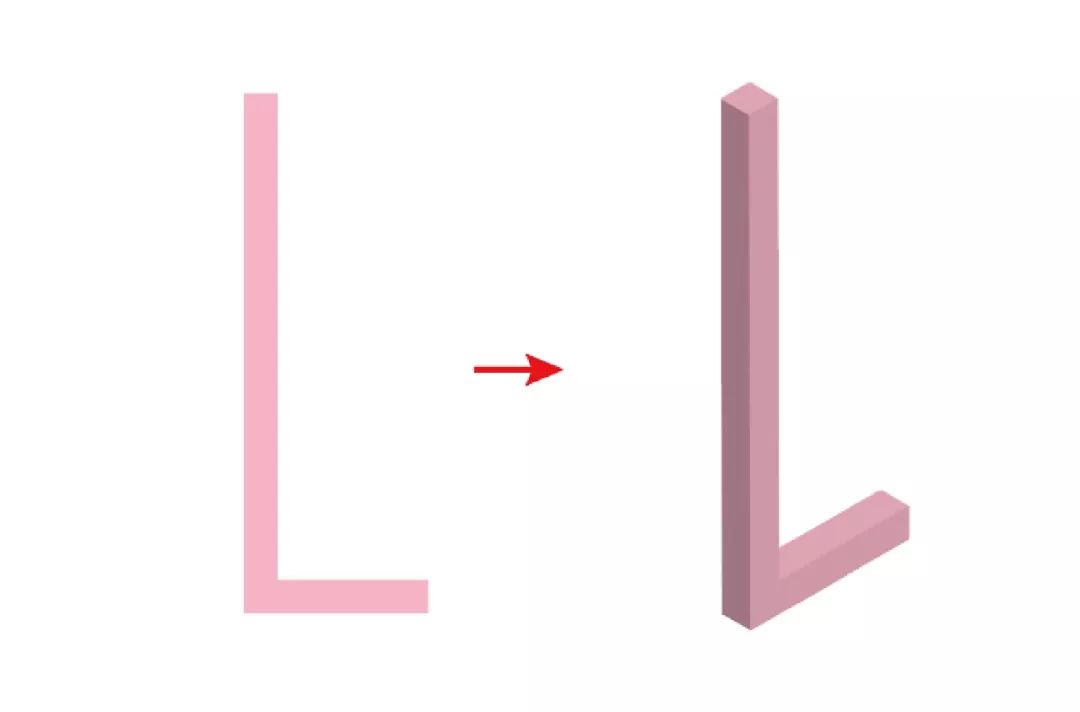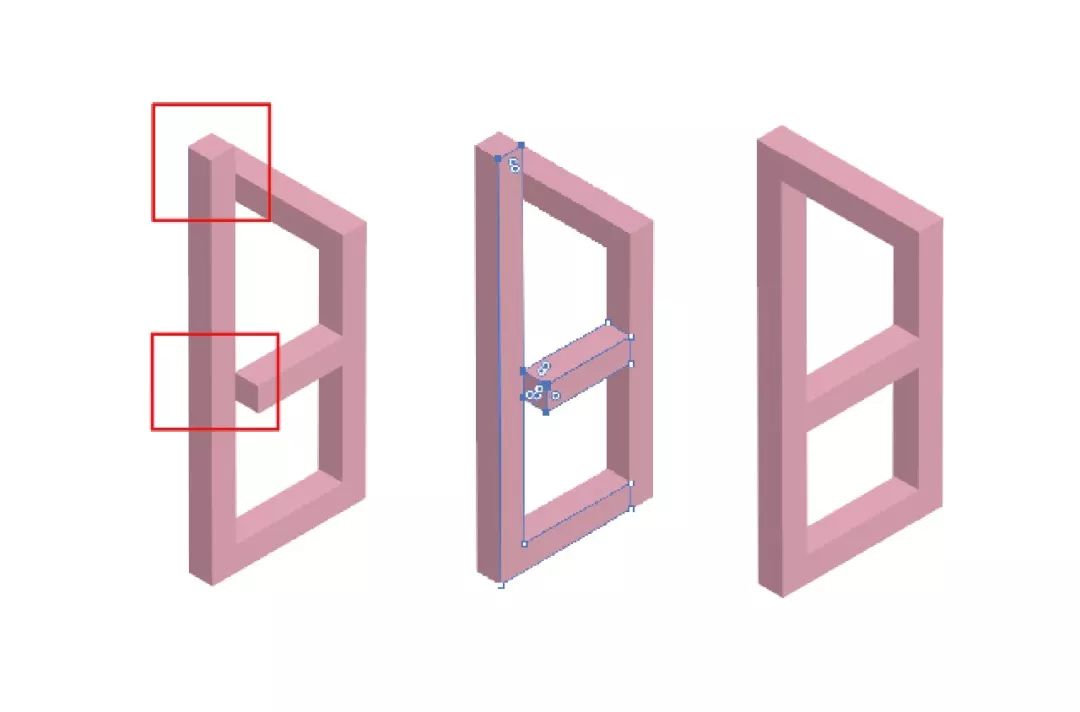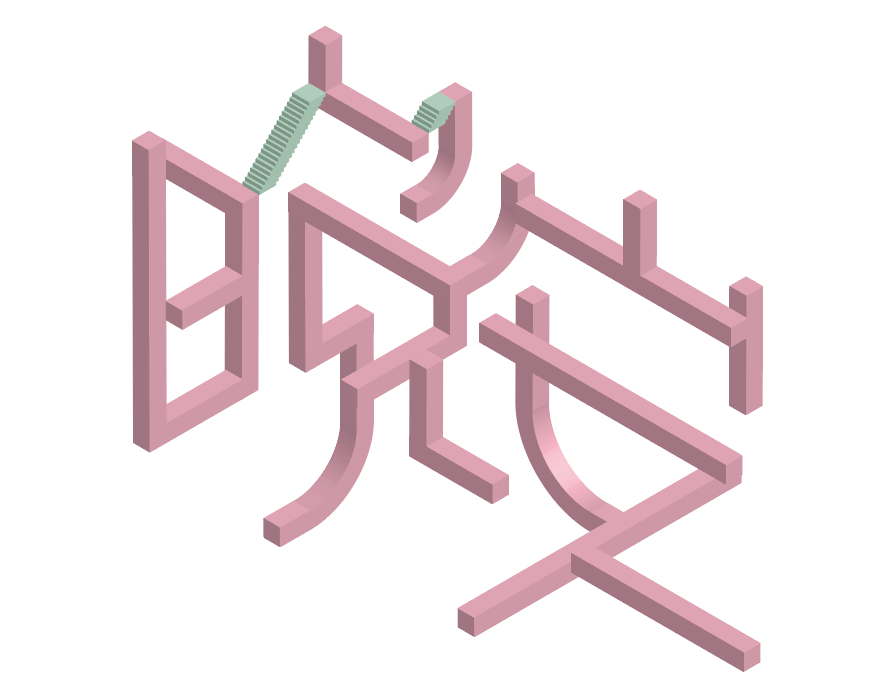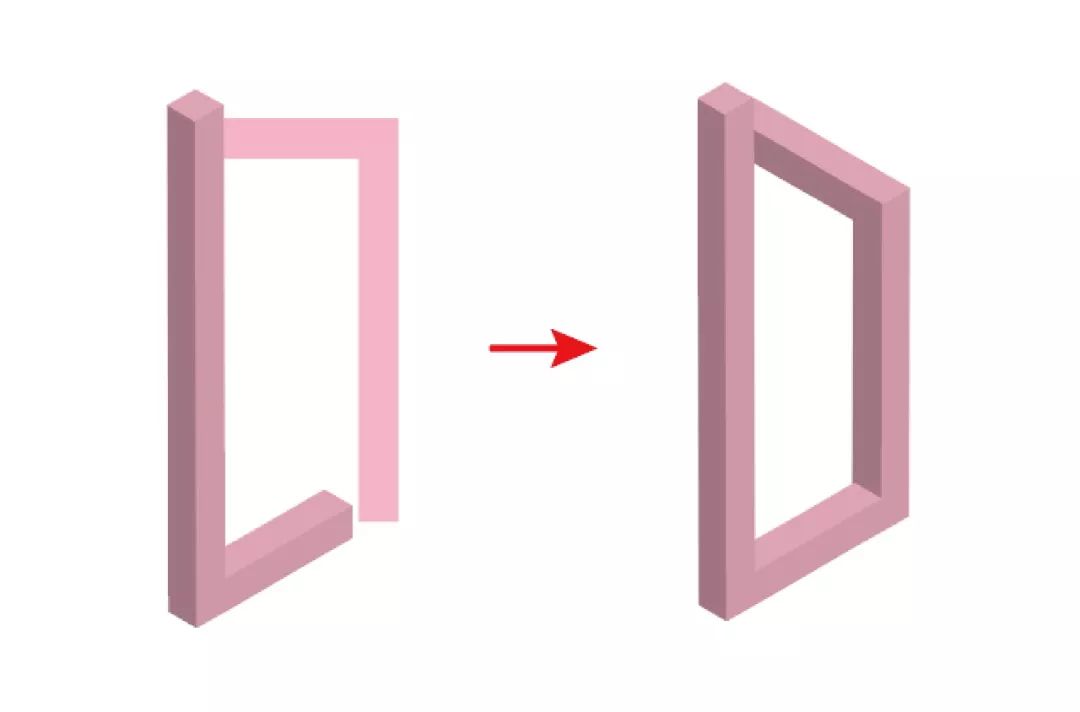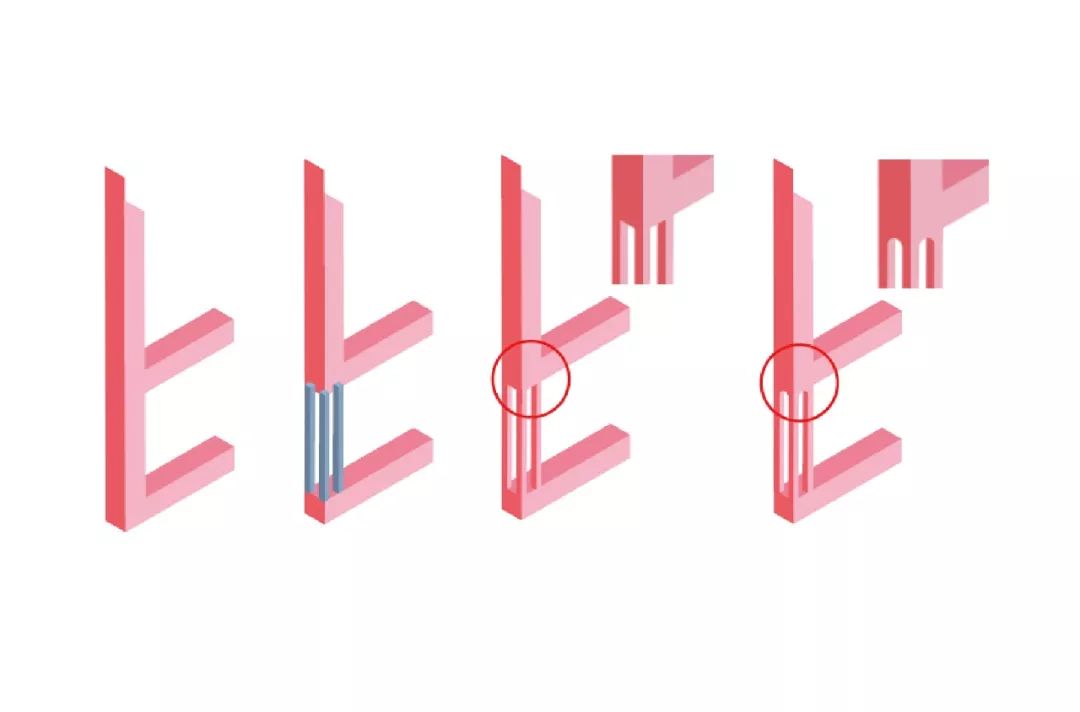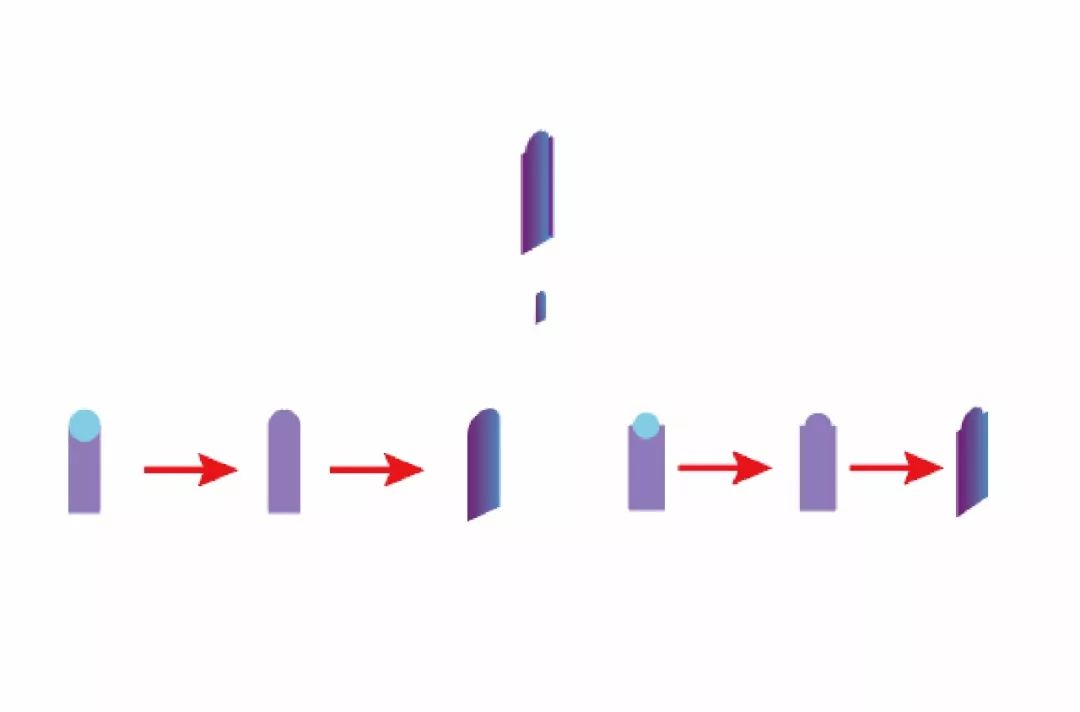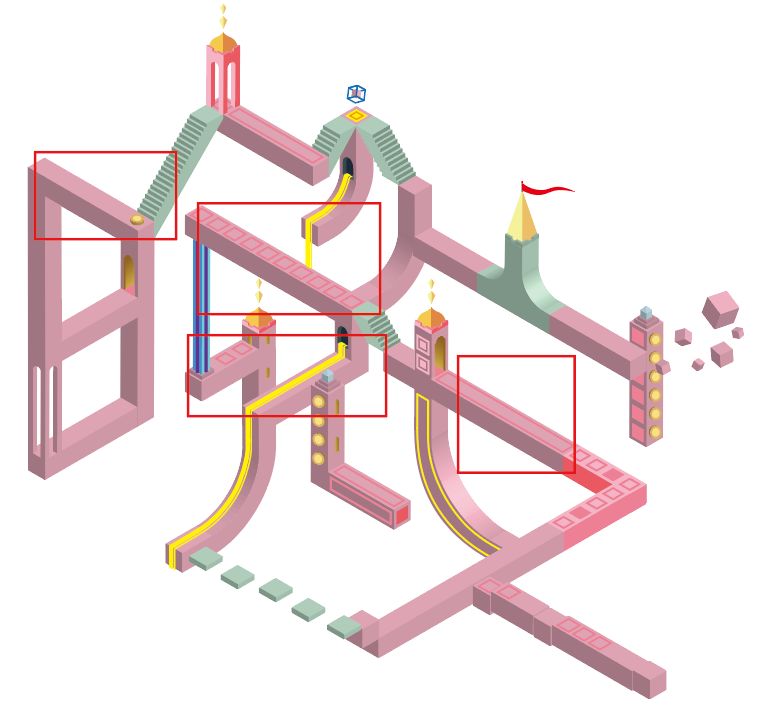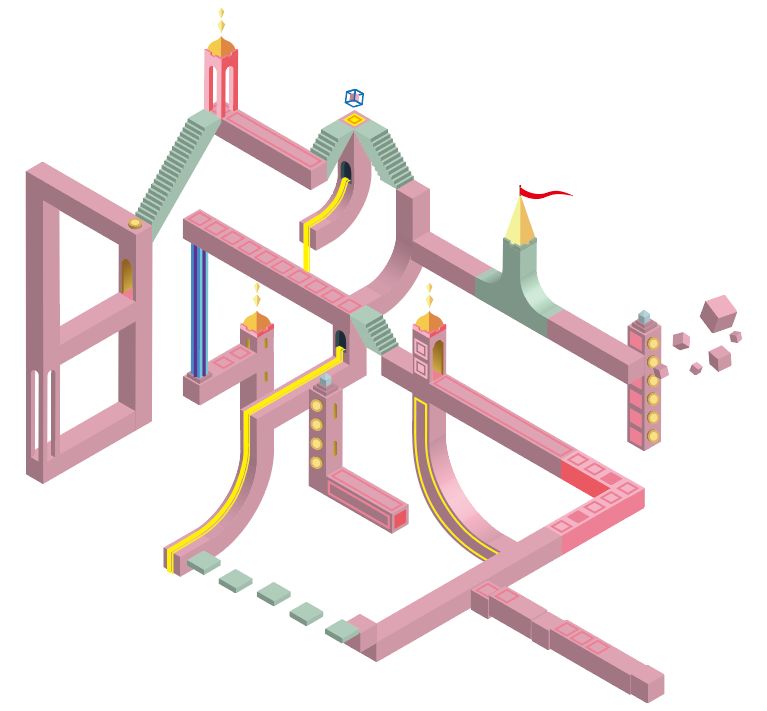
“纪念碑谷”字形设计分析
“矛盾空间”字形字体设计分析
# 基本工具介绍
主要运用钢笔工具和3D工具里的凸出和斜角,那么在凸出和斜角中你会发现有很多选项,其中大部分都用不到,常用的是等角。因为等角的立体角度是一样的,省去很多不必要的功夫。
下面我们来看一下直线在等角后的效果
直线在四个方向的立体化,就会发现“上方”和“下方”的倾斜角度是一样的,所以除去特殊情况,我们就用“左方”和“右方”两个工具就足够了。
# 搭建字型
做这一类字体不像其他平面化或者C4D的纯立体化,如果一开始就想搭建完整组字的字型是不现实的,因为角度倾斜到的位置很难确定,可能在平面阶段看着是正常的,一旦立体处理就会跑到其他位置去了,一个横粗了或者短了都会影响到下一步的操作。所以我建议做一个笔画就立即给它做立体。做修改的话拉锚点也是一样方便的。
按照咱们帮里的老规矩,新建一个1000×660px的画板。开始做第一步,钢笔勾线。描边设置12pt。然后在“效果”窗 口中找到“3D”,选择第一个“凸出和斜角”。然后“等角-右方”。窗口出来后注意“凸出厚度”要跟描边粗细一样,这样才会等宽等高。
第二笔要参考着第一笔去画位置,操作同上,角度选“等角-左方”。
有弧度的笔画在平面阶段要把直角做圆角处理,“直接选择工具”中有圆角工具。适当地拉弧度。
楼梯是由一个个等宽等长不等高的正方体组成的,描边的长度就是它立体化的厚度,一个台阶不宜太高,所以我设置为3pt,其他不变。
照着这些基本操作把剩下的字型完成并略做调整。之后全部选中在窗口“对象”中执行“扩展”,转换为形状。
开始做细化的处理。我想要的是矛盾空间,那么红框的部分就需  要结合到一起。用直接选择工具拖动要被盖住部分的锚点,直到看不见凸出为止。其他相似位置操作也一样。
# 组合元素
“日”字旁我想要一个类似“亭子”的效果。首先需要3根“柱子”,“柱子”的描边宽度和凸出厚度都是3pt,长度能够顶住上下两部分。之后扩展,然后把“日”字被替换部分截去,把柱子安进去。最后把在一个面的图形合并,合并的命令在“窗口”>“路径查找器”第一个。之后还要给“柱子”顶部做一下圆角。因为有透视,所以近处的圆角比远处的要大一点。
为了方便讲解和理解,接下来我就直接把元素和步骤放出来,不再说明是那个位置的了。
做好的小台阶给它一个一个叠加,然后取消所有小台阶的编组,黄色部分合并。套索工具圈中右侧的锚点删除,台阶底部就齐了。
钢笔勾出一个三角形、垂直镜像复制、对齐。
方法同上
描边1pt、长度4pt、凸出厚度2.5pt、比较低的两个为1pt。
一个方块、三根柱子,方法和“日”字旁一样。
方法同上。
圆形+矩形、合并、倾斜工具按住Shift垂直方向调整透视。然后渐变颜色做出空间感。
钢笔12pt、长度自定、凸出厚度12pt。
扩展、合并“人”字面、减去多余锚点。
钢笔顺着弧形勾出一条线,再复制出一条稍微细一点的线,扩展形状后调整端点的边缘倾斜角度。
小正方体的角度不必那么规整, 毕竟是漂浮的,可以随意选择 角度立体化,显得灵活一点。然后扩展。
复制一个前面的正方体,放大一些填充无、描边1pt,扩展合并。
椭圆工具画出一个正圆形,凸出厚度2.5pt,扩展外观、取消编组,原位复制上面的椭圆形并缩小。换个颜色。
很规则的平行四边形是由正方体拆分后的一个面得到的。
拿出正方体左边的面复制出一个并缩小,原来的面填充无, 内描边0.75pt后扩展并编组。
原理同上,正方体的上面一个不动,另一个内描边0.75pt。
#丰富场景与上色
基本元素和方法都已讲解完,来看一下组合起来大致的效果。
所有的笔画都是一样粗细,显得有些呆板,是不是可以给局部做缩窄或加宽的处理呢?来、接着搞。
红框里的我都往上缩了8pt,看着和桥差不多,灵动的同时也丰富了画面。
然后把画面丰富一下,人物放进去,适当地再放些装饰元素。
填色要先确定光源,我把光设定在右上方。朝上的面就是亮面右边是灰面,左边就是暗面。
一般描边扩展完后都会自动编组,想要填色的话都必须是单个对象。这里有两个方法,一是鼠标右键取消编组,点完后继续右键,接着点取消编组,因为它往往会有好几个编组。二是双击鼠标左键(或者单击右键)进入隔离模式,在隔离模式下可以对单个对象进行操作,就可以填色了。
关于快速填色的技巧,可以用魔棒工具点中,它会自动识别相似的颜色并选中,但也有个缺点,差别不大的颜色也会在它选择的范围,所以魔棒的使用视颜色情况而定。
这里几个有弧度的需要用到颜色渐变,AICC2019中渐变有个非常好用的功能“任意形状渐变”,可以自由地布置渐变的路线。
最后给背景也做自由渐变。
色值参考如下:
最后,来看一下完成稿: